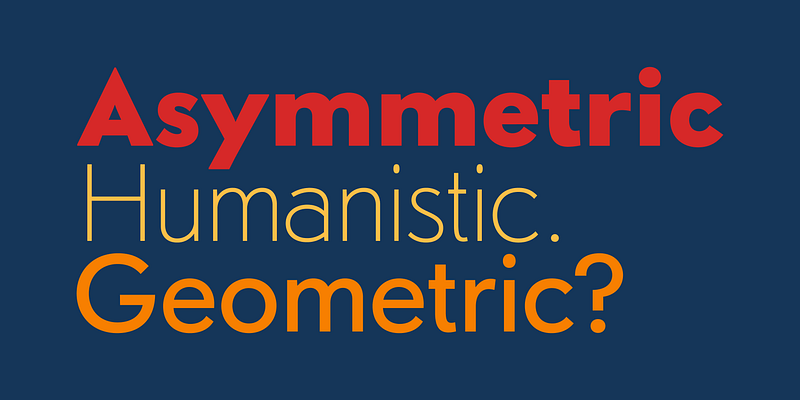
Sonar Sans ist der Versuch, die Regel der geometrischen, historischen Form mit dem vergebenden, menschlichen Ausdruck frühgotischer Schriften zu vereinen. Nichts an dieser Schrift ist wirklich symmetrisch. Die geometrische Natur des zugrunde liegenden Modells diente lediglich als Ausgangspunkt, um die Formen einer kontrastarmen Erweiterungsschrift zu finden.